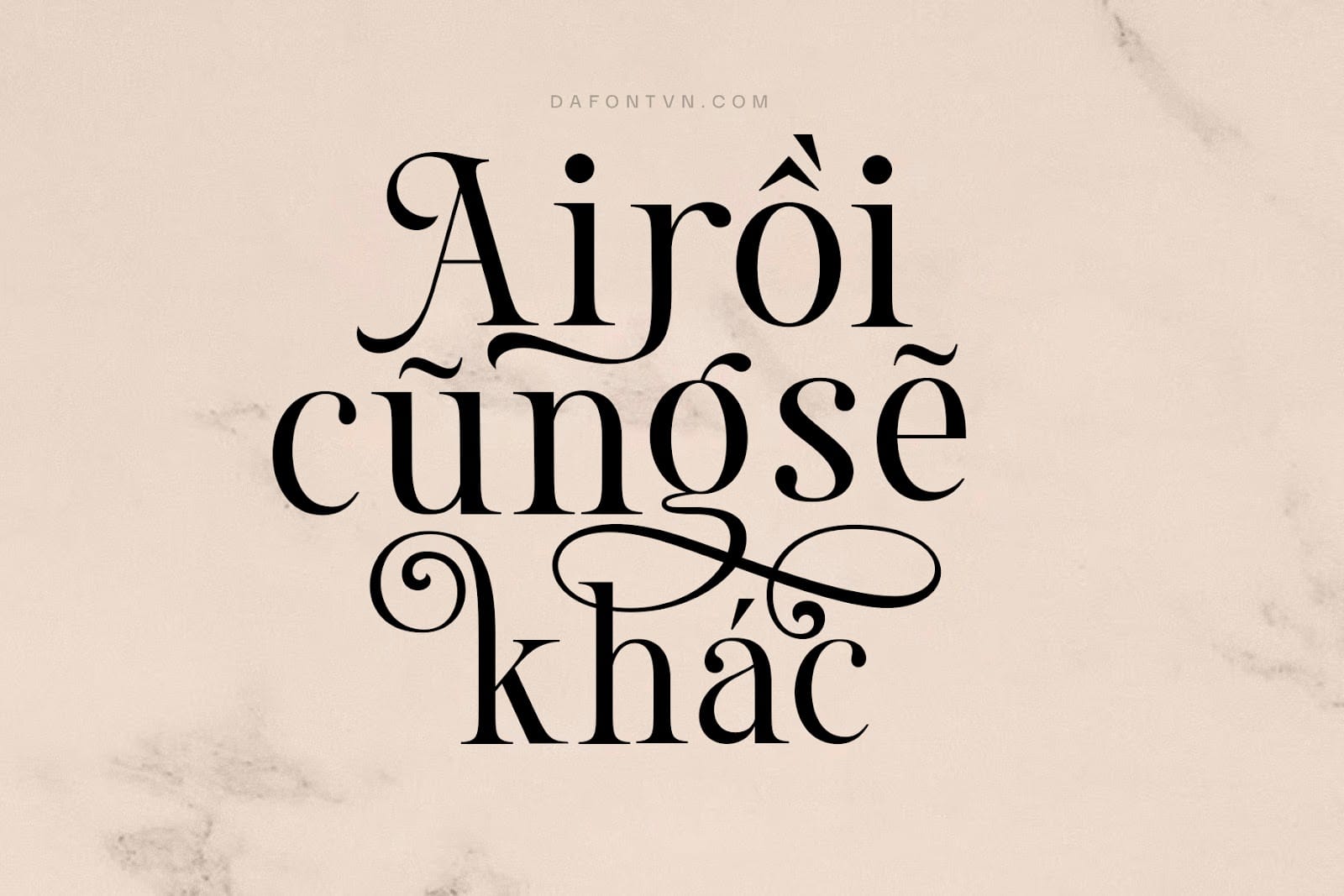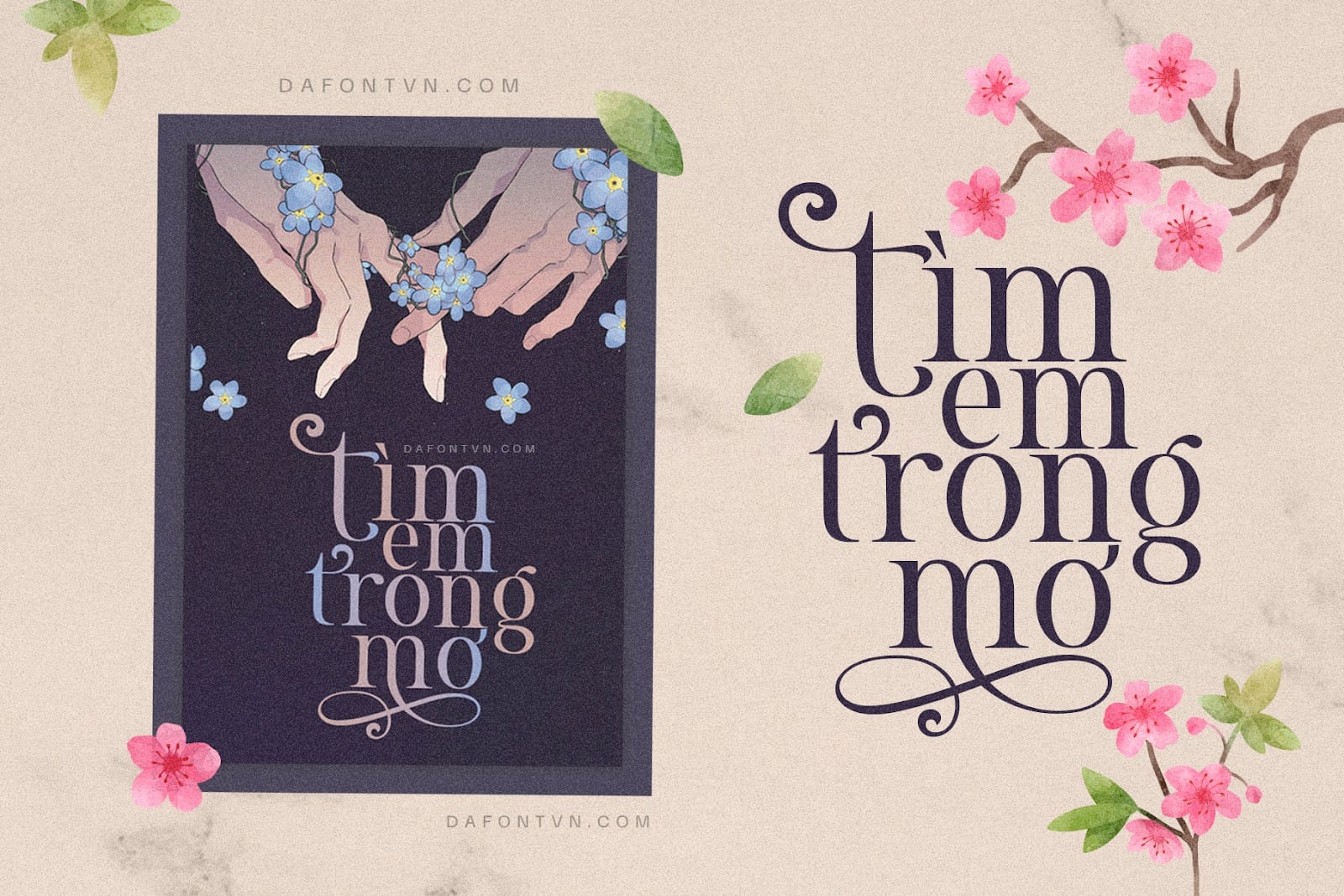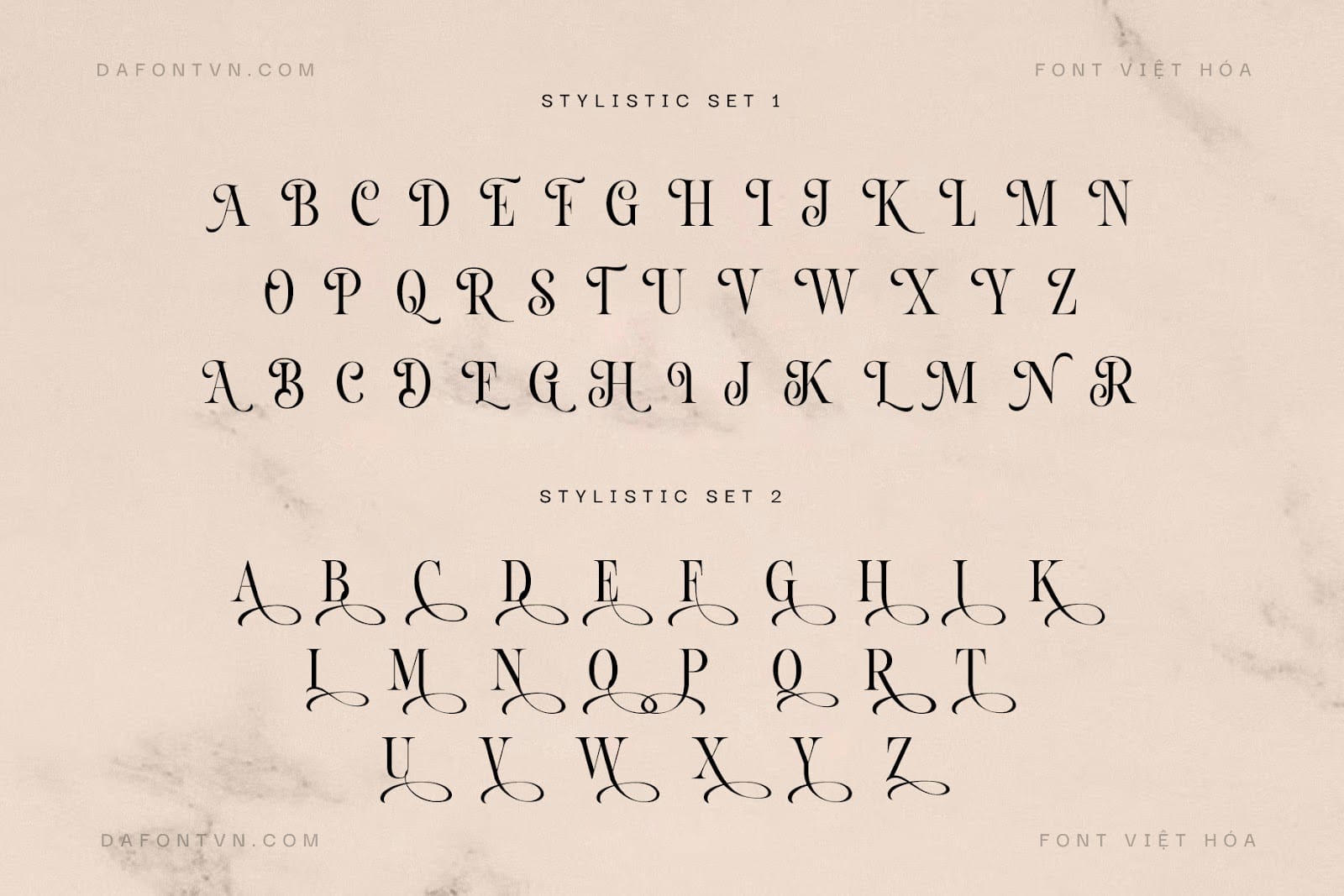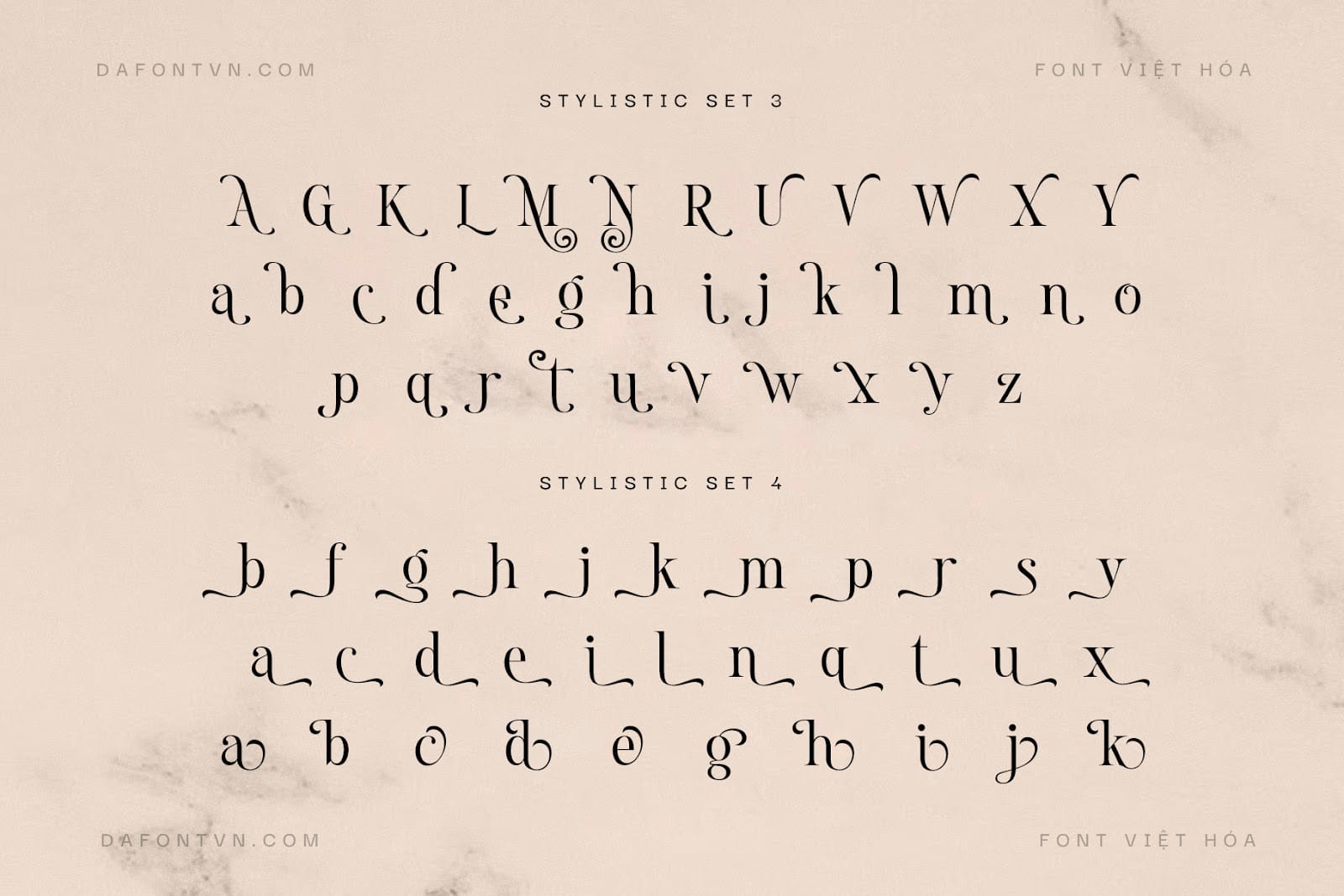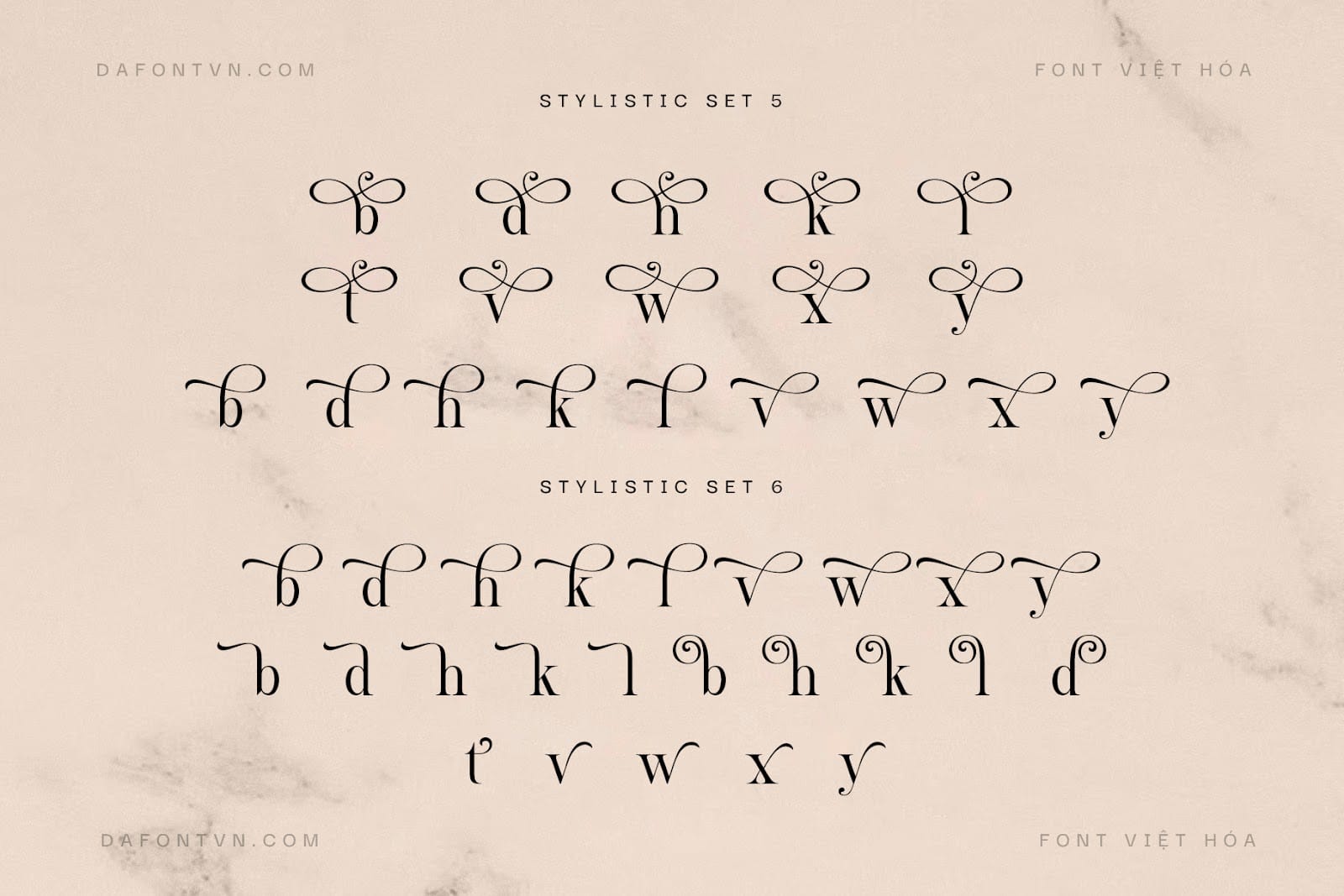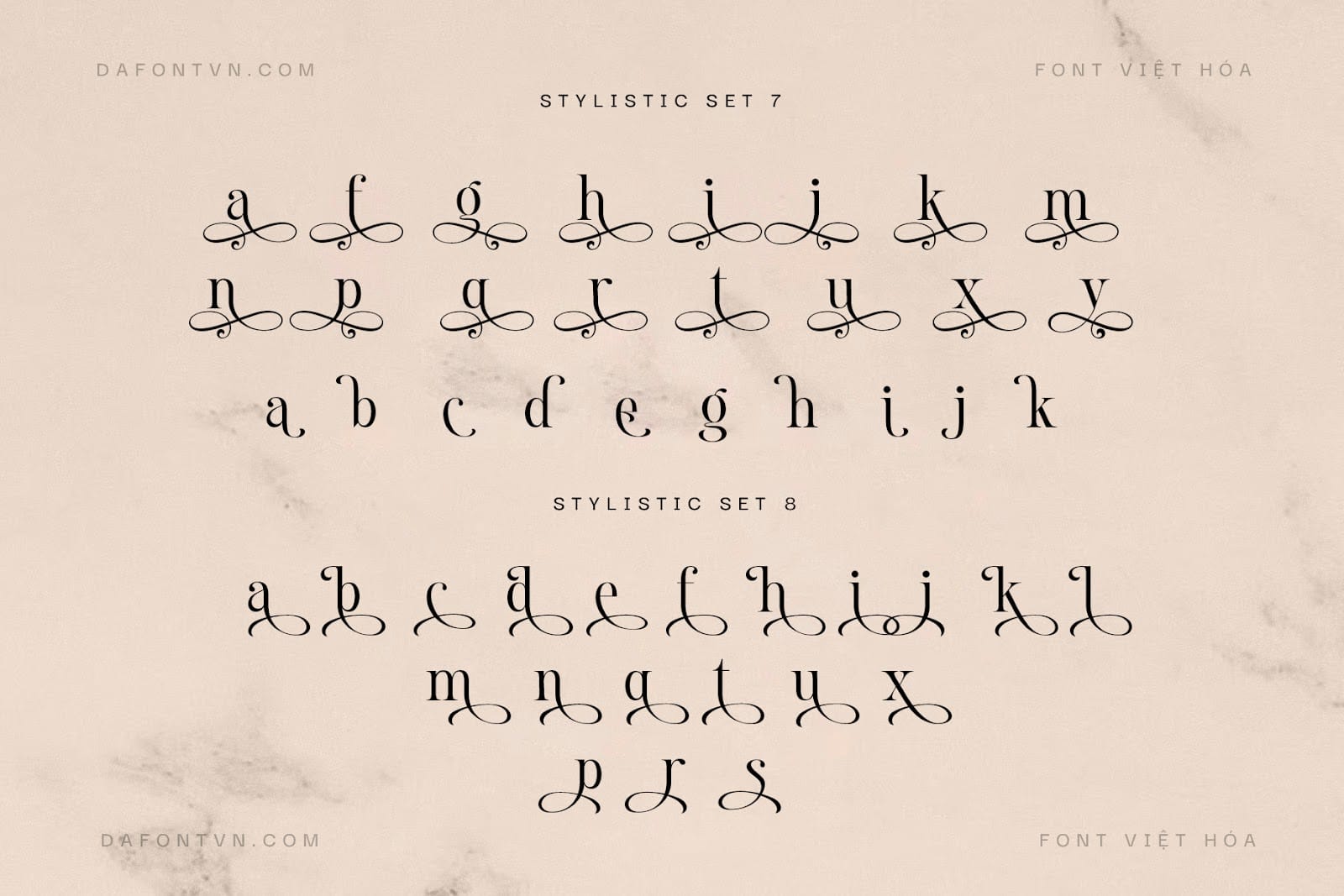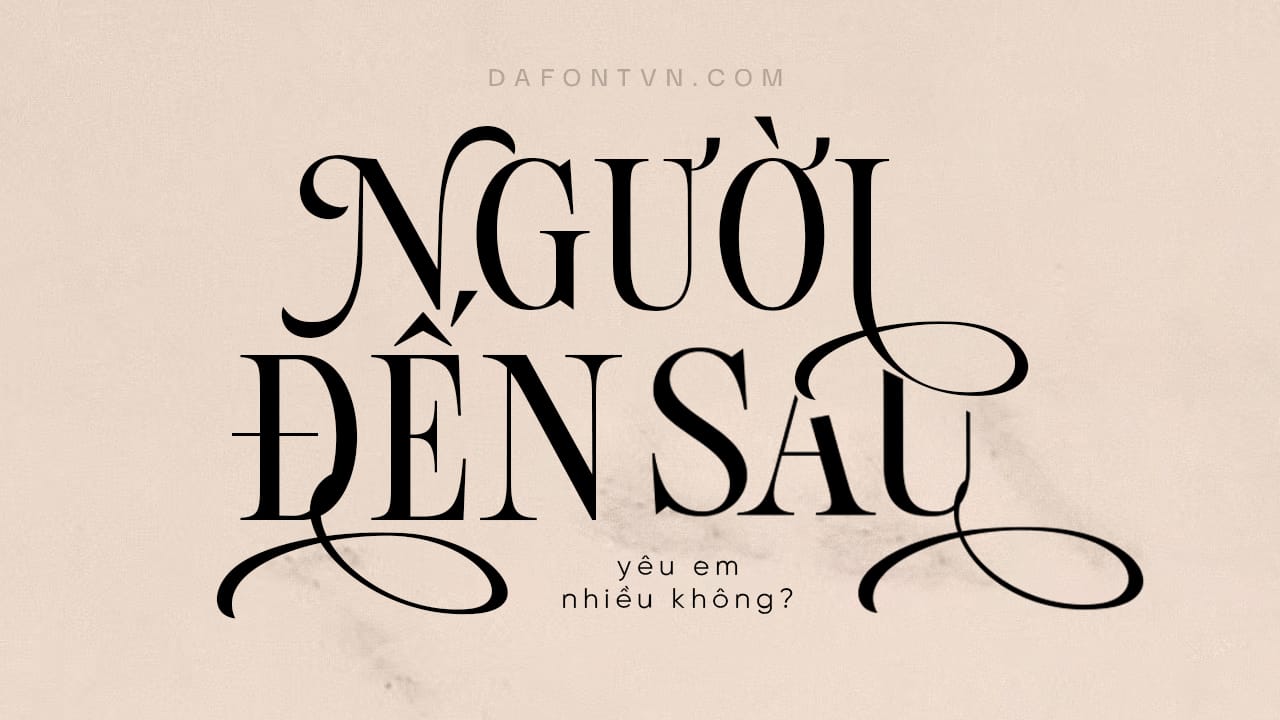
Font Việt hóa Faith cực đẹp bao gồm hơn 1000 glyph để bạn tha hồ sáng tạo.
Font Faith là 1 kiểu serif hiện đại với các đường nét cứng cáp của chữ in hoa và 1 chút mềm mại của chữ thường vì vậy dễ dàng áp dụng cho bất kỳ thiết kế nào, đi kèm với các glyph uốn lượn đẹp mắt mang đến cho bạn 1 kiểu font chữ tinh tế, ấn tượng và hoàn hảo cho nhiều thiết kế khác nhau như bìa sách, typography, tiêu đề, quảng cáo, thiệp mời…
Font Việt hóa đầy đủ, kerning, chỉnh sửa và tối ưu lại cũng như mã hóa PUA để sử dụng hầu hết trên các phần mềm. Ngoài ra, font có 2 kiểu dấu khác nhau cho kiểu Ư và Ơ các bạn thích kiểu nào thì dùng nhé.